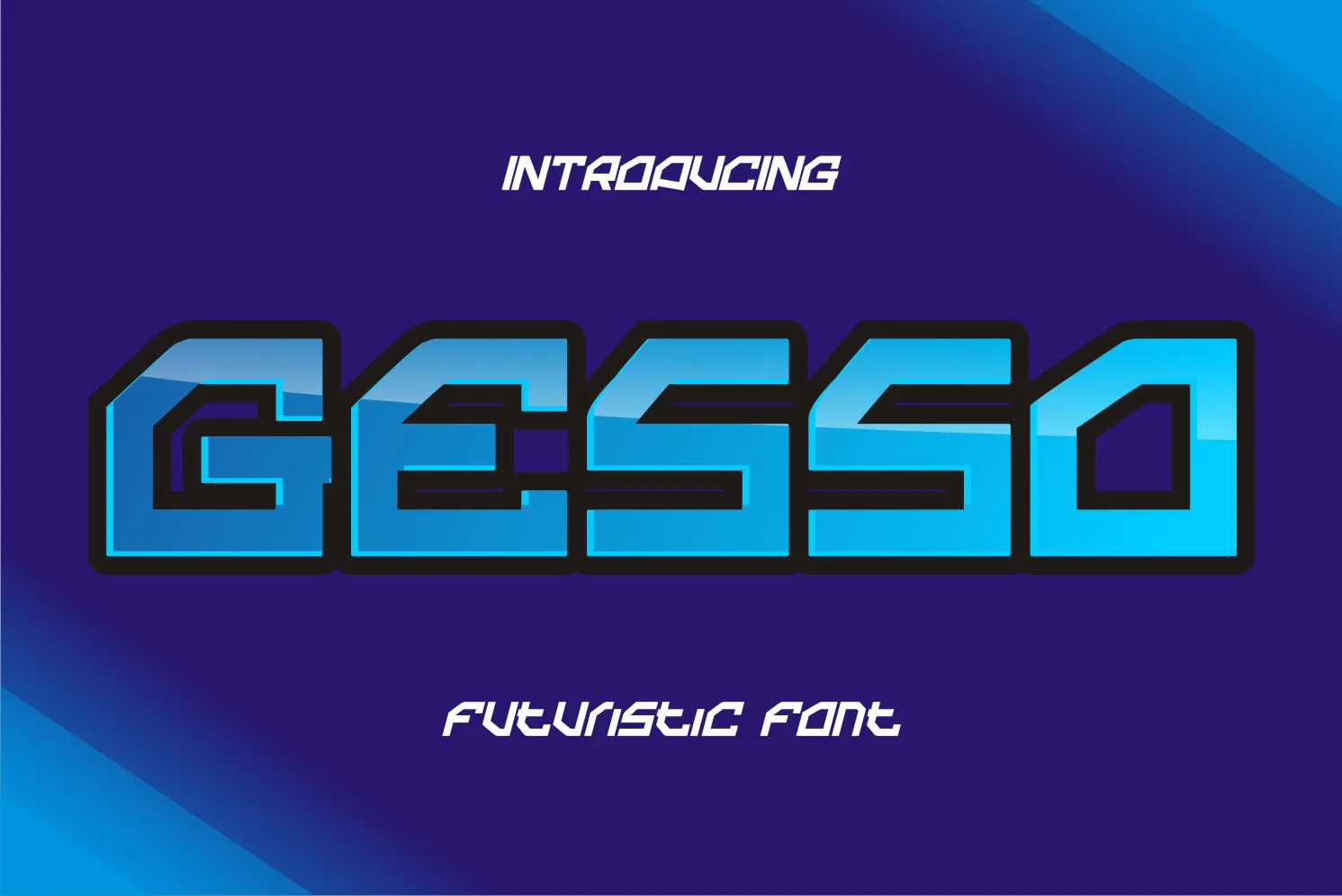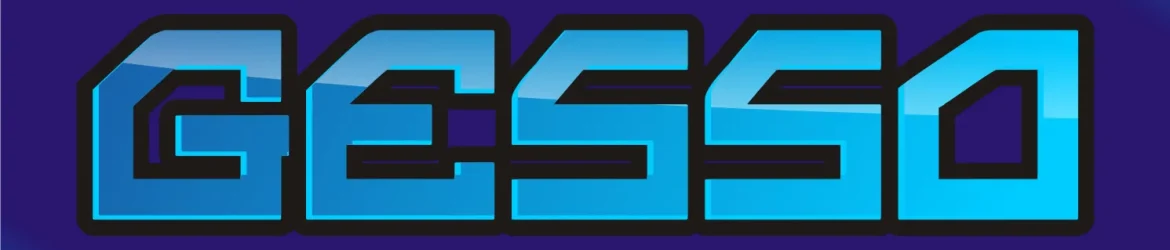
Gesso Font – Download Grátis
A fonte Gesso Font é uma escolha ótima para quem procura algo moderno e futurista para dar seu design web ou cartão de visita aquele toque único. Desenvolvida pelo designer letterfiastudio, esta fonte está disponível na categoria de Fonts Display e se destaca por sua aparência tecnológica e criativa. Ideal para usar em elementos visuais que exigem um aspecto futurista e inovador, seja ele para uma página web ou para um cartão de visita, Gesso Font é a escolha perfeita. Com seus traços leves e linhas retas, esta fonte não apenas adiciona um toque moderno, mas também transmite uma sensação de velocidade e inovação. Perfect para quem busca dar aquela pitada extra de originalidade à sua identidade visual digital ou física.